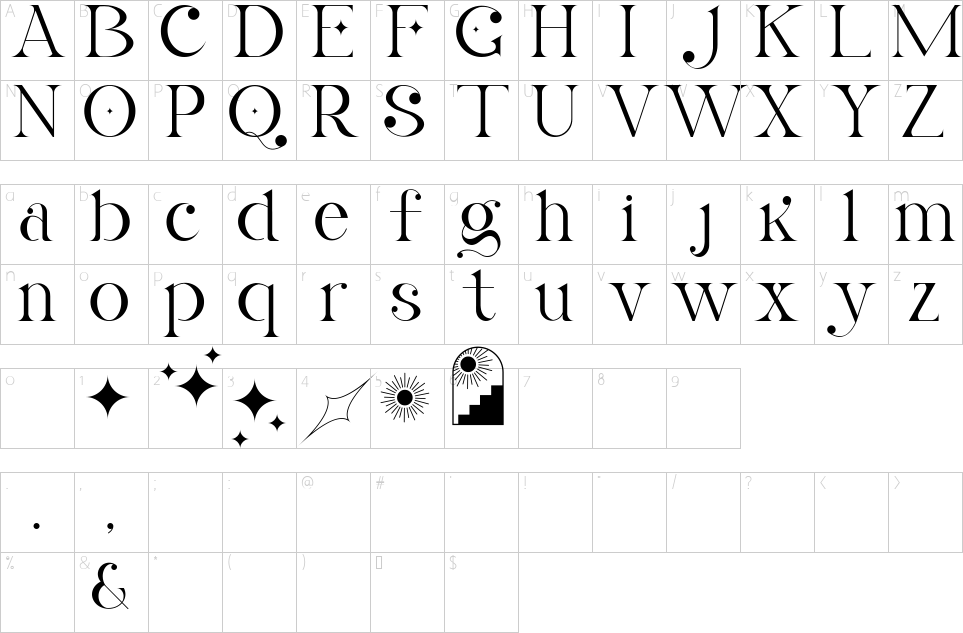
A fonte La Obrige é uma opção perfeita para designers gráficos em busca de uma fonte moderna e elegante, com um visual suave e agradável aos olhos. Desenvolvida pelo designer indiano Putu Dody Permana, La Obrige oferece um conjunto de caracteres versátil e versátil, que se destaca por sua harmonia entre linhas leves e formas simples. Este fonte é ideal para uso em designs digitais, como logotipos, publicações online, e websites. Com seu design limpo e fácil de ler, La Obrige se adapta perfeitamente a diversos projetos de design, oferecendo uma escolha excelente entre as centenas de fontes gratuitas disponíveis. A fonte La Obrige já foi baixada 620 vezes, evidenciando seu valor e popularidade entre os designers. Se você está procurando por uma fonte que se destaca entre as tantas opções disponíveis, La Obrige é uma ótima escolha.